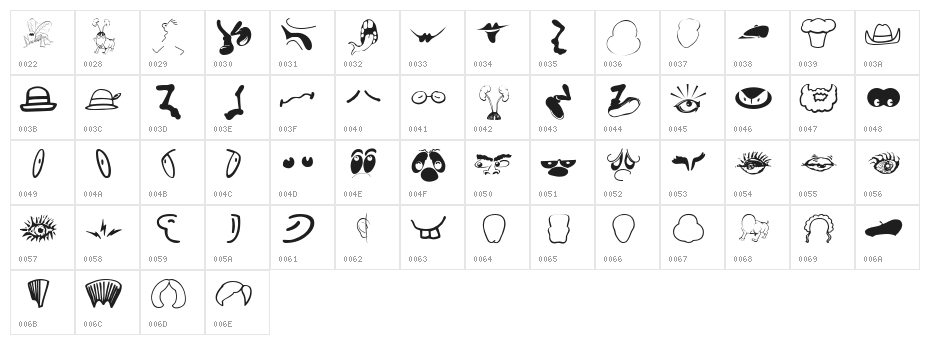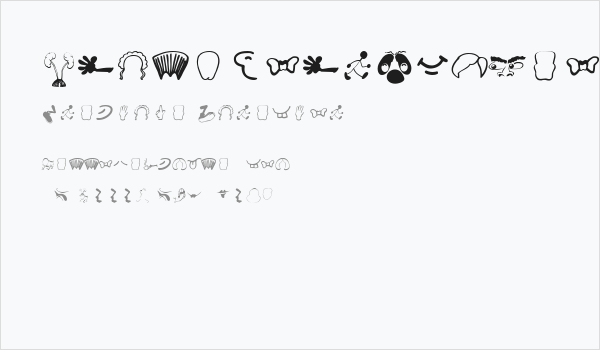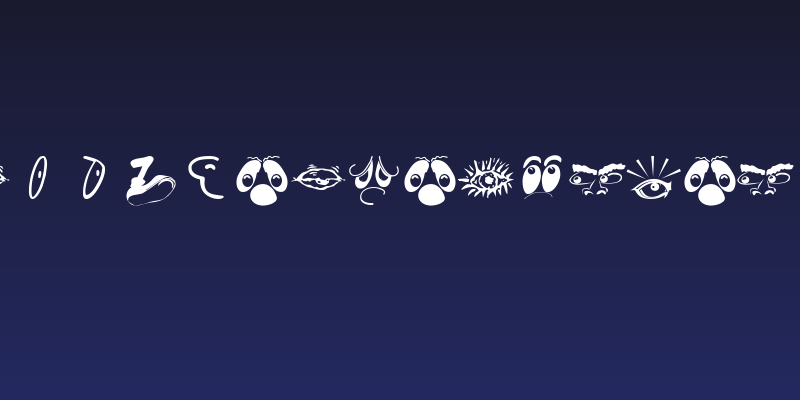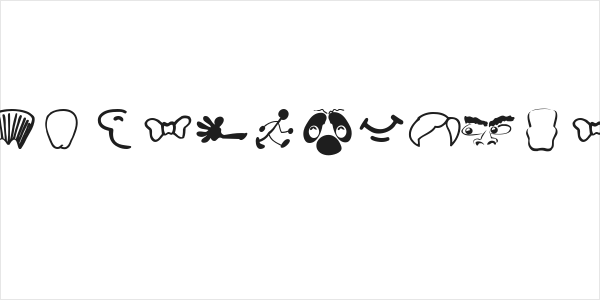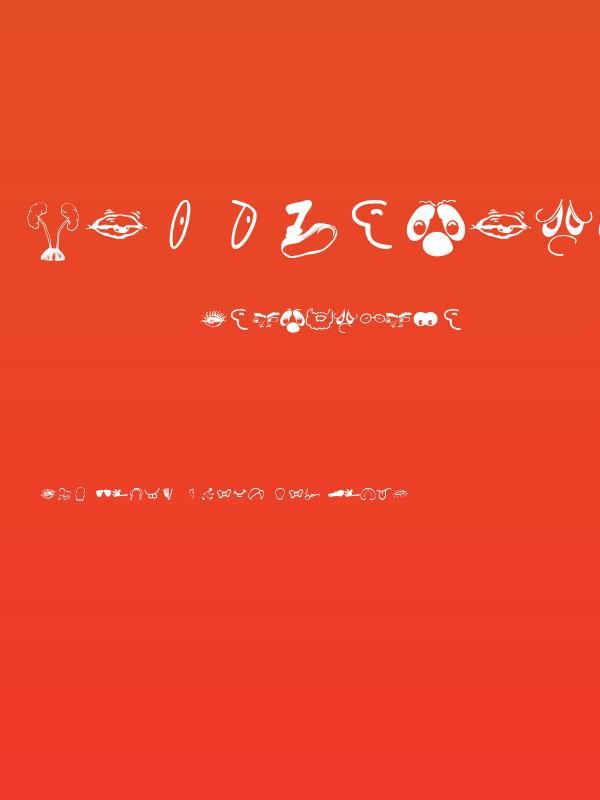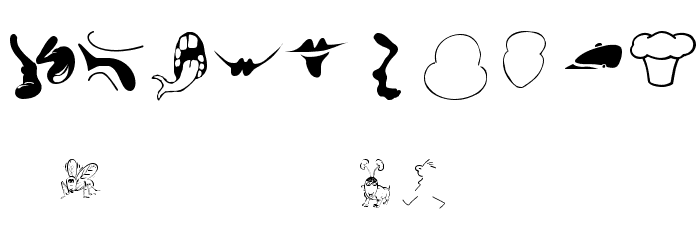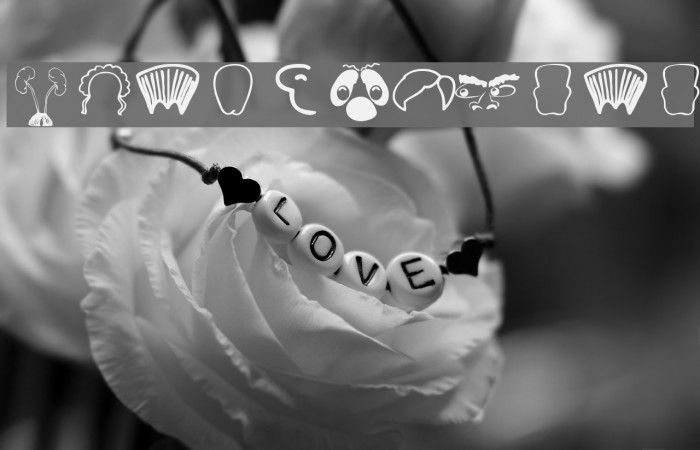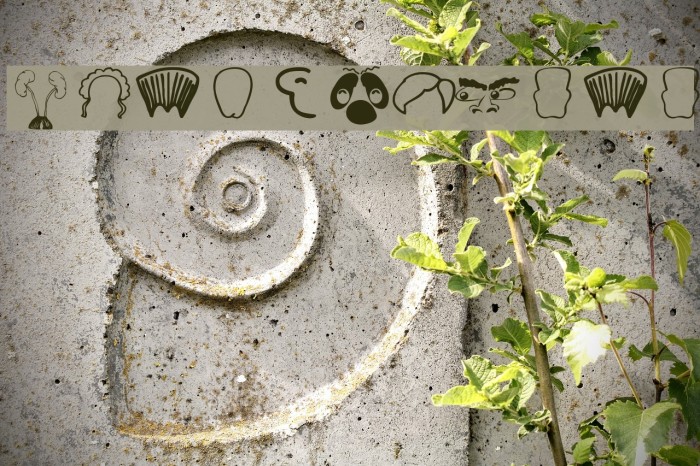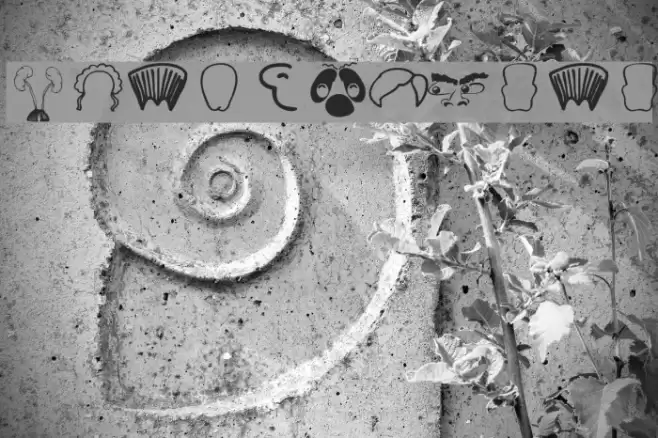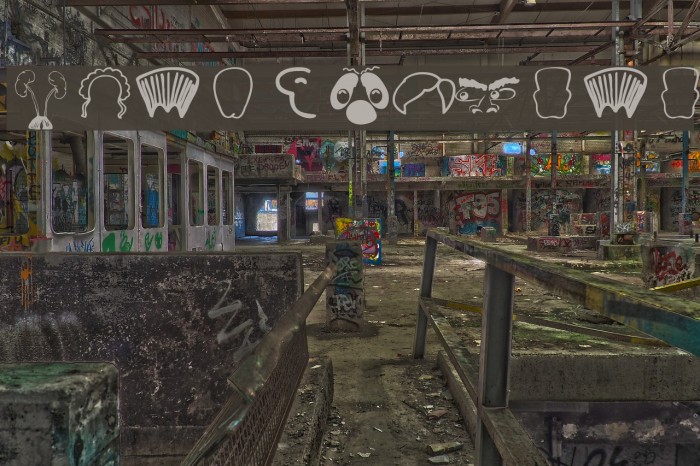
BuildYourOwnPeople Font
| Gesamtstil | Playful, Whimsical, Cartoonish |
| Anwendungsfall | Illustrations, Games, Educational tools, Creative projects |
| Vorgeschlagene Projekte | Children's activity books, educational materials, creative workshops, party invitations, playful branding, and custom avatar creation. |